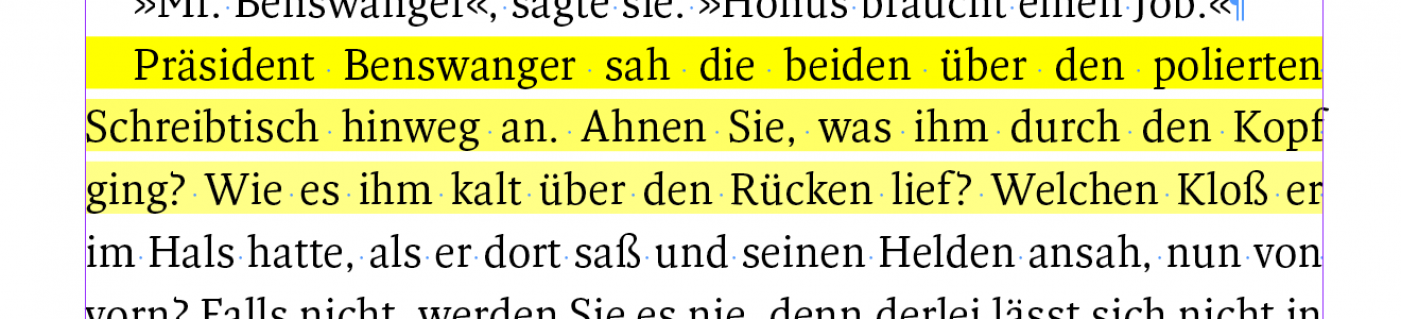
Austreiben/Einbringen im Blocksatz
bisher habe ich im Blocksatz Hurenkinder und Gassenbildung aufgrund riesiger WZR meist durch das Erhöhen bzw. Verringern der Laufweite vermieden. Nun ist das ja eigentlich verpönt, da dadurch der Grauwert geändert wird, auch wenn ich die LW »behutsam« um maximal  5 Einheiten (in InDesign also um 5‰ eines Gevierts) anpasse.
Wie ist da euer Workflow? Arbeitet ihr mit der Anpassung der Wortzwischenräume? Kann man das in ID irgendwie überblicken? Ein Eingabefeld wie für die LW, die man dadurch immer im Auge behält, gibt es ja m.W. nicht.
Anbei ein konkretes Beispiel mit einer sehr unschönen, löchrigen Zeile (die WZR wurden hier von ID auf ca. 200% erhöht) und der Frage, wie ihr in so einem Fall vorgehen würdet.
Meine Einstellungen sind bei diesem Screenshot wie folgt: Wortabstand: min. 85%, opt. 100%, max. 130% — Zeichenabstand: 0% — Silbentrennung: min. 5 Buchstaben, kürzeste Vorsilbe: 2, kürzeste Nachsilbe: 3, max. Trennstriche: 3 — Schrift: Fresco Normal 9/13, ca. 62 Zeichen pro Zeile.
Meine Antwort ist mit Vorsicht zu genießen, da ich, was Gestaltung und Layout angeht, Autodidakt bin.
Meine Einstellungen in InDesign (CS5) .
Abstände: 80%, 100%, 110%
Silbentrennung: 3, 1, 1, 1,  5 und der Schieberegler steht ganz links auf »Abstände optimieren«.
Meine Silbentrennungseinstellung geht gegen alle Empfehlungen, funktioniert aber so recht gut. Ich habe bisher nur äußert selten nachbessern müssen.
Danke für Deine Antwort! Leider sieht mein Beispiel  mit Deinen Einstellungen  genauso schlimm aus wie vorher. Und Wörter mit drei Buchstaben zu trennen, bringe ich nicht über’s Herz. ;—) Wie treibst Du denn Zeilen aus bzw. bringst sie ein?
Trotz meiner »furchtbaren« Silbentrennungsoptionen ist es noch nie vorgekommen, daß ID ein dreibuchstabiges Wort getrennt hätte.:roll:
Ich fürchte, bei dem von Dir gezeigten Abschnitt wirst Du mit dem Ergebnis leben müssen. Ich sehe keine Möglichkeit, wie Du »Schreib-« auf die erste Zeile bringen könntest. »ging« ist auch nicht viel besser. Vielleicht hat ja hier noch jemand einen Tipp, wie tief man in die Trickkiste greifen müßte. Ich lebte damit. Auch deshalb, weil eine aufwändige Lösung vielleicht nur »halbgut« aussieht und diese zwei Zeilen geschafft wären, es aber durch diesen Eingriff  »weiter unten« zu neuen Problemen führte.
Bei Mengentext kommt es mir in erster Linie auf das angenehme Lesen an und erst in zweiter Linie darauf, wie die Seite im Ganzen wirkt. Deshalb achte ich im Zweifelsfall eher auf »sinnvolle« Silbentrennungen als auf einen möglichst gleichmäßigen Grauwert.
Deshalb achte ich im Zweifelsfall eher auf »sinnvolle« Silbentrennungen
So mache ich das auch, da ich die schnelle und möglichst eindeutige Erfassbarkeit vorziehe.
Was macht ihr denn bei Hurenkindern? Treibt ihr Zeilen aus bzw. bringt diese ein, indem ihr die LW verändert? Greift ihr in die Breite der WZR ein? Verändert ihr den Satzspiegel minimal in der Breite (±1mm) oder in der Höhe (±1 Zeile)? Und falls ja, in welcher Reihenfolge bzw. in welcher Priorisierung?
Bei mir war das bisher so (InDesign, Blocksatz, klassische Literaturformate):
1. LW ±5
2. Die beiden untersten Zeilen einer Doppelseite entfernen (also Länge des Satzspiegels ändern)
3. Wenn die Paginierung nicht im Weg ist und der Übersatz max. 1/3 der Zeilenlänge hat, eine zusätzliche Zeile unter den Satzspiegel einfügen
4. LW ±10 (zur Not und mit Bauchschmerzen)
Das schlaue Buch (»Detailtypografie«) sagt ja, dass man beim Austreiben/Einbringen garnicht mit der LW, sondern mit den WZR arbeiten soll.
Was macht ihr denn bei Hurenkindern?
Einfach zwei Zeilen zusammenhalten :-D
Das ist zu einfach. Gemeint war vermutlich: Was kann man tun, damit der Satzspiegel bei der Methode des Zeilen-Zusammenhaltens nicht um eine Zeile zu kurz wird?
<schmutzige Tricks>Wenn du sehr unglücklich mit den großen Wortzwischenräumen bist, kannst du für den einen Absatz mit Zeichenabstand (-2%/0%/2%) und Glyphenskalierung (98%/100%/102%) experimentieren und sogar den Schriftgrad um 0,1 Punkt reduzieren. Typographen werden aufjaulen, aber sieh dir das Endergebnis an und entscheide dann, was für dich insgesamt besser aussieht. Du kannst auch für die eine Seite den Satzspiegel um z.B. 1 mm verbreitern (oder schmaler machen), das merkt auch fast niemand.</schmutzige Tricks>
Ich hab mal in Corel etwas ganz anderes probiert. Ich weiß, Schriften strecken und stzauchen ist Bä! Aber warumj eigentlich nicht etwas ausnutzen, das ja jetzt erst durch digitale Schriften geht, und in Blei schlicht unmöglich ist. Im grunde ja der werg, dfen man bei alten Handschriften nutzte, indem man nicht nur die Wortzwischenräume, oder auch zu unterschiedlichen Grauwerten in den Zeilen führend, die Laufweite ändert, sondern die kompleete Zeile streckt oder staucht?
Weil ich mich damit gerade wieder rumschlage: Ist das nicht die Typografisch beste Lösung? Die minimale Verbreiterung ist doch nicht auffällig und so wurde doch auch früher (Gutenberg-Bibel) auch gesetzt. Persönlich gehe ich nicht unter 99%, das dann doch zu viel. Aber eine leichte Verbreiterung finde ich nicht störend, wenn es zu besserer Worttrennung führt. Meistens bekommt man ein Hurenkind ja weg, indem man einen Absatz vorher anders umbricht und nicht das eigentliche Hurenkind zurechtstutzt.